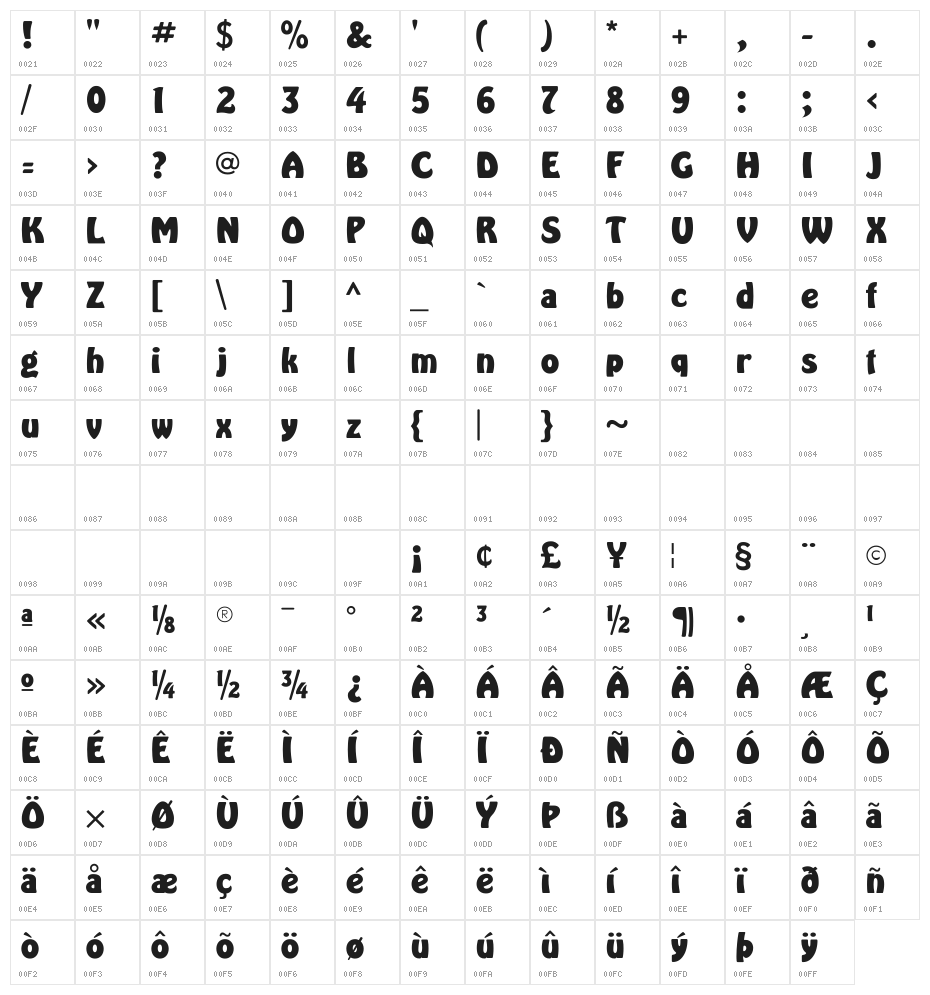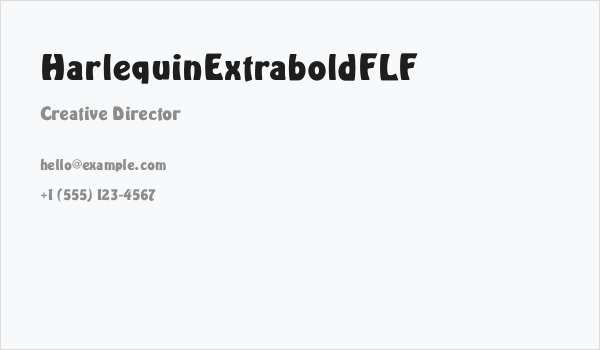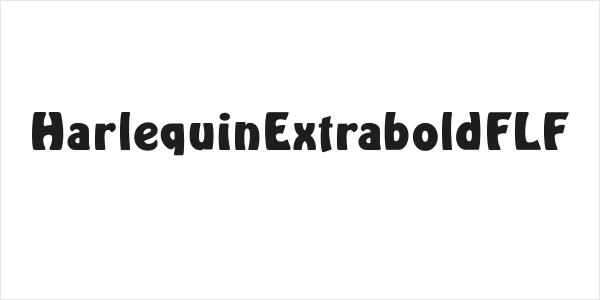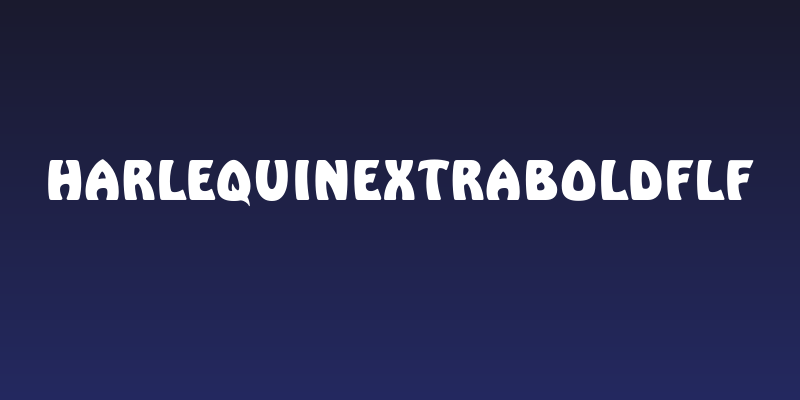
HarlequinExtraboldFLF Font
| Gesamtstil | Playful, Whimsical |
| Vorgeschlagene Projekte | Ideal for children's books, playful branding, posters, and creative advertising. |